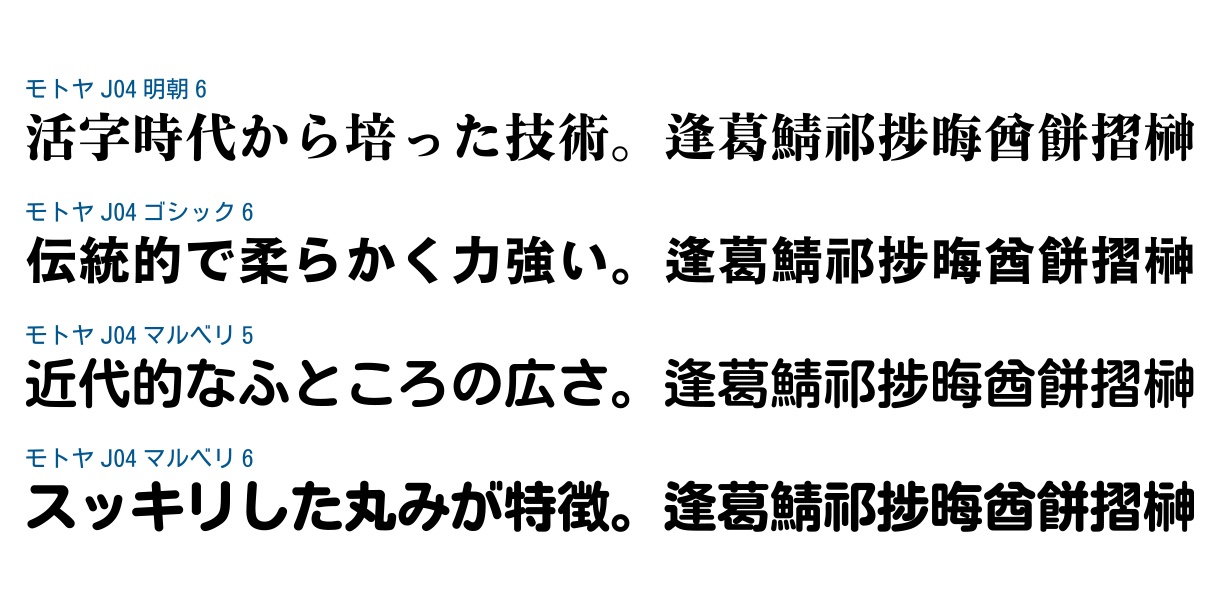
Monotype、年間定額制フォントサービス「モトヤ LETS」に4書体を追加
米国 Monotype Imaging Inc.の日本法人Monotype株式会社(東京都港区、以下 Monotype)は、年間定額制フォントサービス「LETS Leading Edge Type Solution」のライブラリ「モトヤ LETS」および「学生向けモトヤ LETS」にて、すでに提供している株式会社モトヤの「JIS X 0213:2004対応フォント」に、新たに「モトヤJ04明朝6」「モトヤJ04ゴシック6」「モトヤJ04マルベリ5」「モトヤJ04マルベリ6」の4書体を追加しました。
※JIS X 0213:2004とは…
JIS漢字コード規格の一つ。JIS漢字コード規格は日本語をデジタル機器で扱えるように、どのようにコードを与えるかという符号化を規定する工業規格です。中でもパソコンや携帯電話などで使われ一番普及しているJIS漢字コードで、6,879文字を規定した「JIS X 0208」という規格があり、「JIS X 0213:2004」とはその規格の拡張版で11,233文字を規定しています。
<株式会社モトヤ>のコメントモトヤLETSにすでにご提供している「JIS X 0213:2004対応フォント」に、今回新たに「モトヤJ04明朝6」「モトヤJ04ゴシック6」「モトヤJ04マルベリ5」「モトヤJ04マルベリ6」の4書体を追加いたします。これにより、「モトヤJ04明朝」「モトヤJ04マルベリ」はそれぞれ全5ウエイト、「モトヤJ04ゴシック」は全4ウエイトの展開となり、より幅広いニーズにお応えできるラインナップとなりました。 JIS X 0213:2004対応フォントは、JIS X 0208から追加された漢字と非漢字を収録しており、さらに例示字形の変更への対応も行っています。そのため、例えば企業内での文書作成などのビジネスシーンでもご使用いただけます。 |
【提供書体一覧】
| 書体名 | 新規追加書体 | ウェイト |
| モトヤJ04明朝 | ・モトヤJ04明朝6 | 全5ウェイト |
| モトヤJ04マルベリ | ・モトヤJ04マルベリ5 ・モトヤJ04マルベリ6 | 全5ウェイト |
| モトヤJ04ゴシック | ・モトヤJ04ゴシック6 | 全4ウェイト |